在生活中处处可以看到艺术字的存在,艺术字广泛应用在宣传、广告、商标、标语、企业名称,以及商品包装、装潢、各类广告、报刊杂志和书籍等,深受广罗大众的喜爱。
艺术字就是以汉字作为基础,经过设计师的创意加工的新型字体,更加美观有趣,醒目张扬,更容易识别字体 。
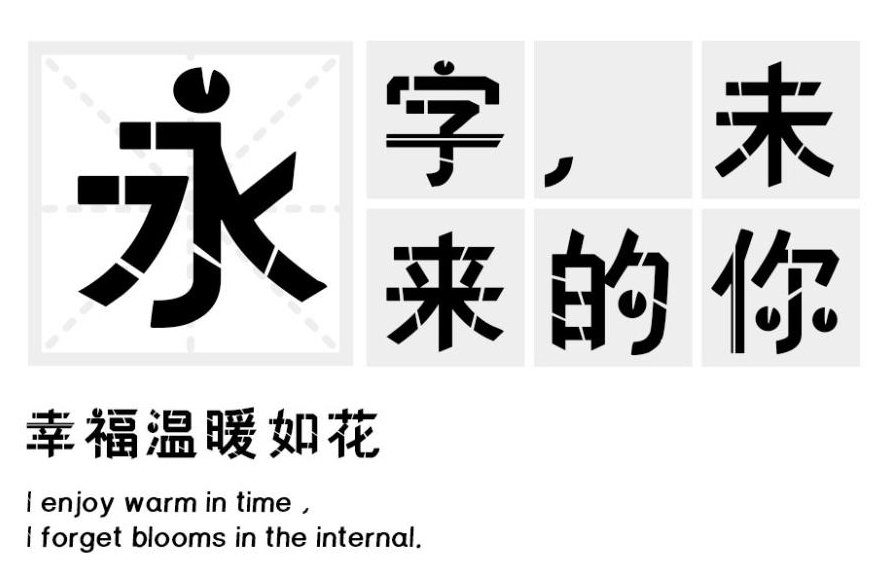
汉标高光黑:这款字体根据黑体的字形创作而来,设计师通过大量剪裁设计字形,展现出撕裂感,美术视觉的高光感,蕴含着深沉的艺术魅力。适用于艺术设计、平面宣传、包装印刷、图形设计等领域。
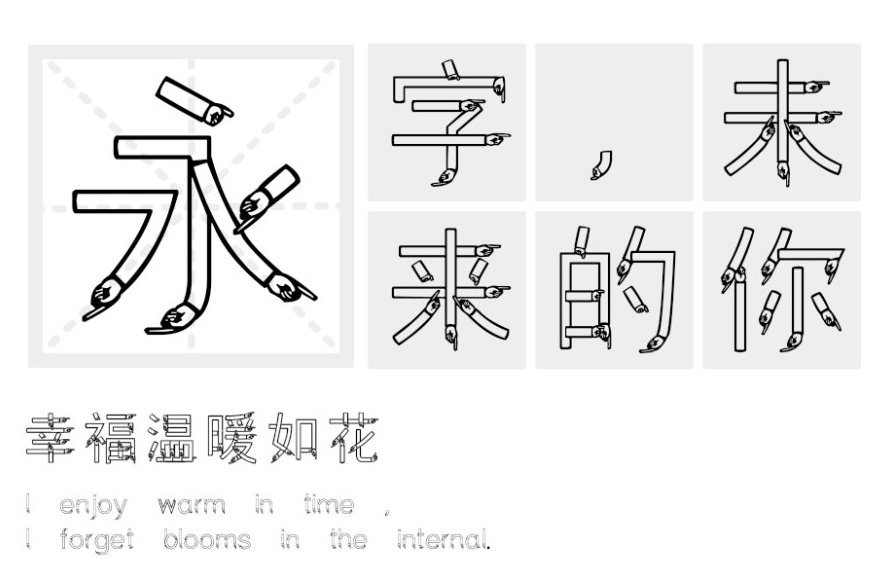
汉标空心手体:这款字体极具艺术设计感,笔画的末端都使用手势图形的元素来构成的,设计师还把这些笔画做成了空心,概括为飘逸的手指向,使左右舒展笔画对称。通常适用于:游戏字体设计、广告设计、屏幕显示等方面。
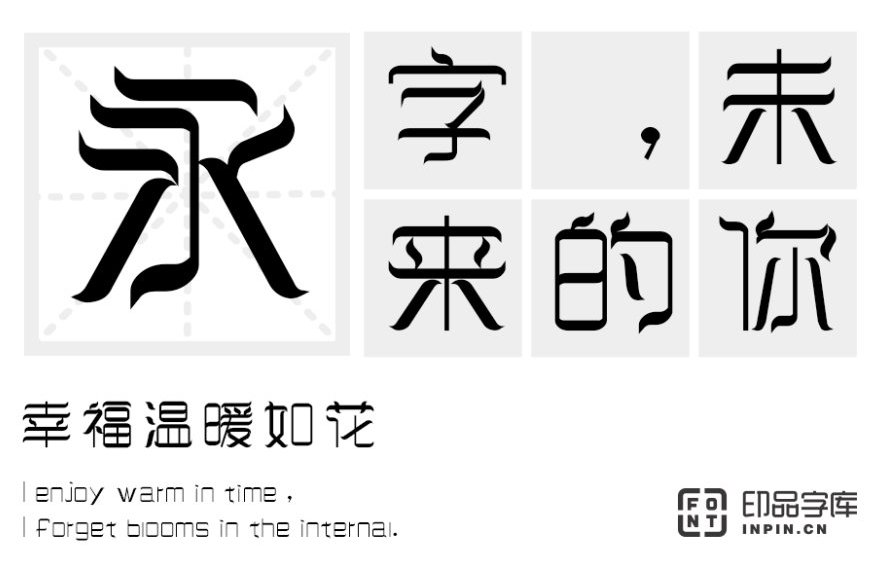
印品飘艺体:这是一款自带美颜效果的字体。横撇点勾处设计仿佛一根丝带。字里行间透露出骨感,让字体有一种在风中自由摇曳的感觉,艺术气息十分浓郁。适用于广告设计、封面设计、艺术设计等领域。